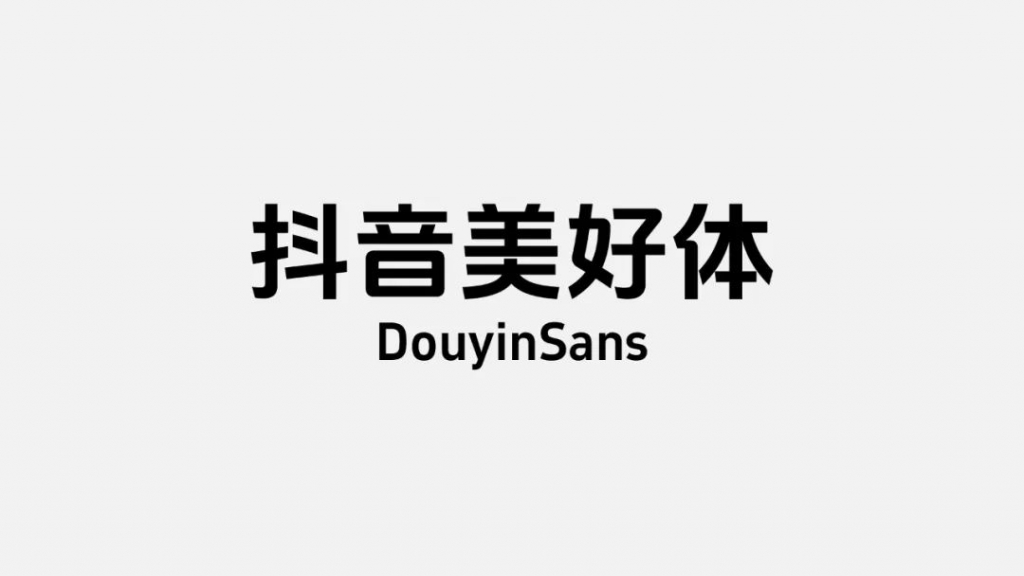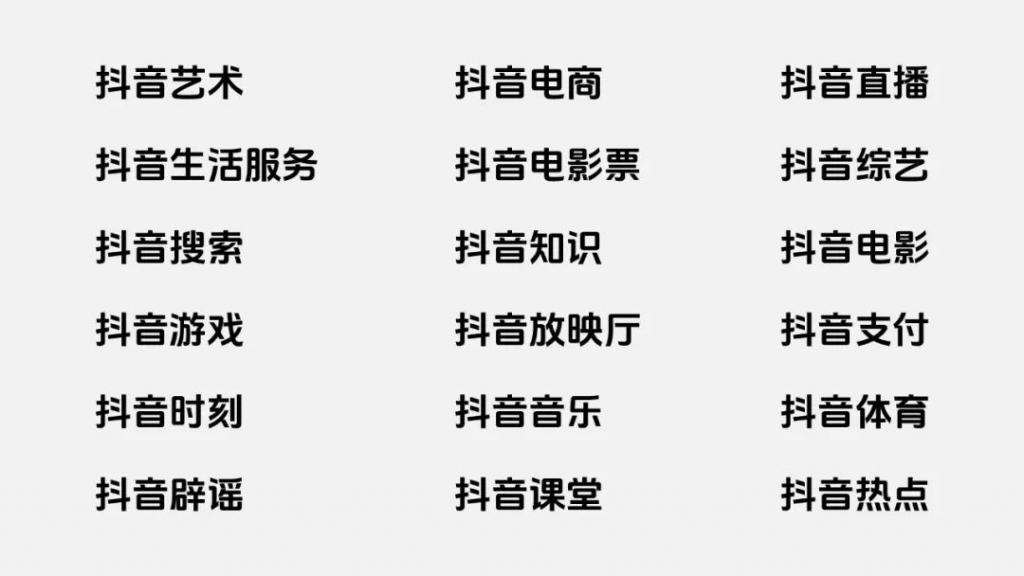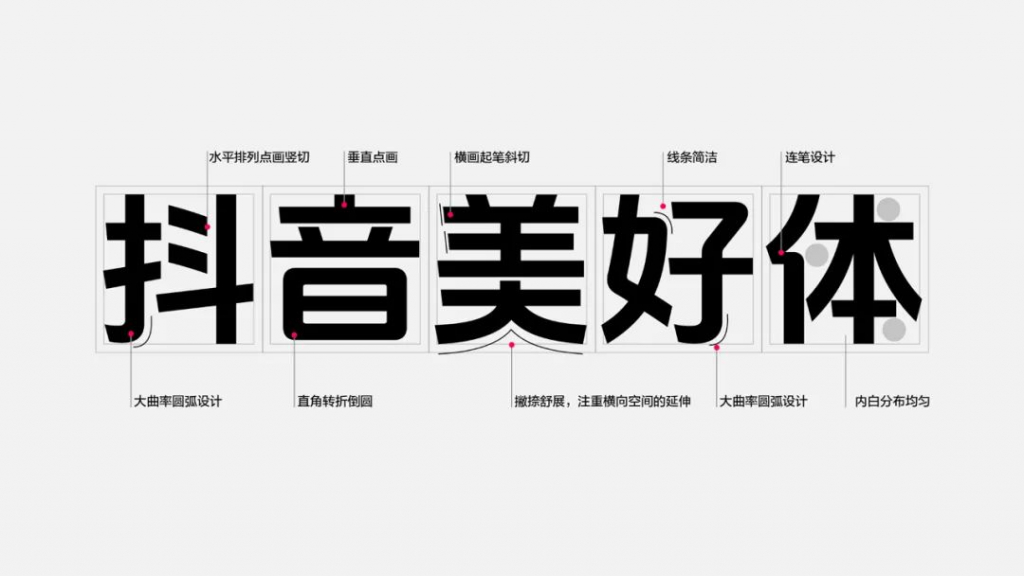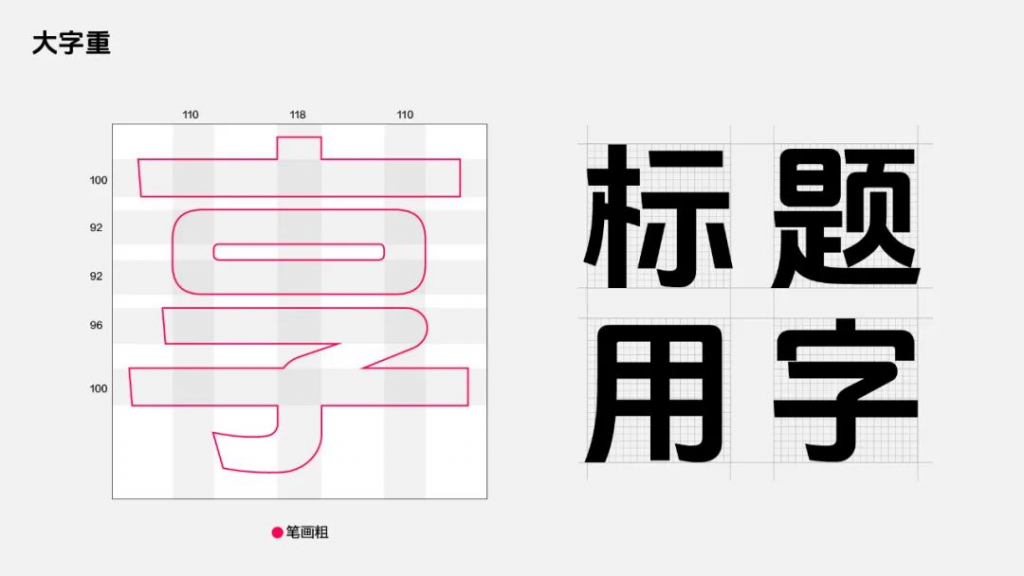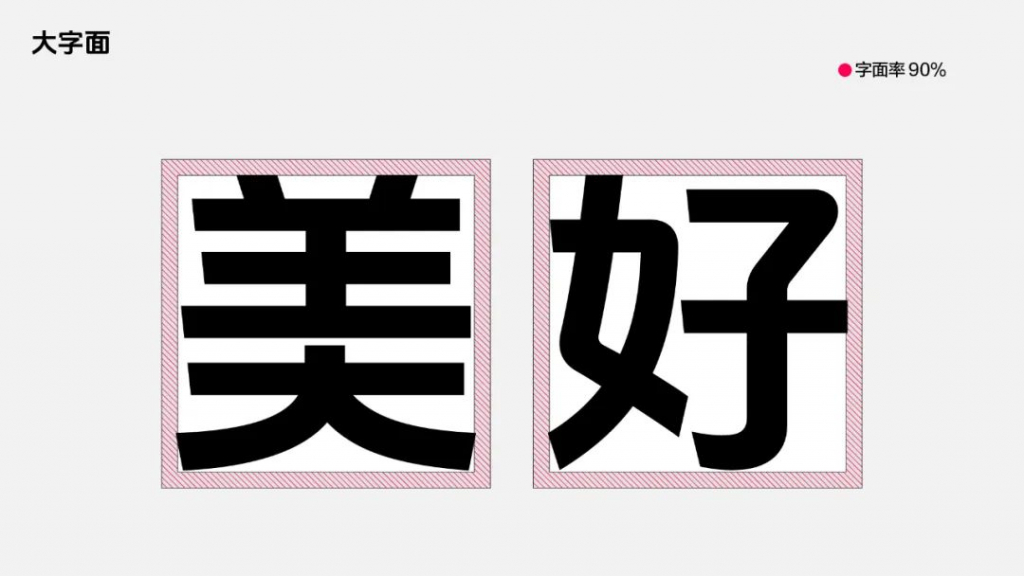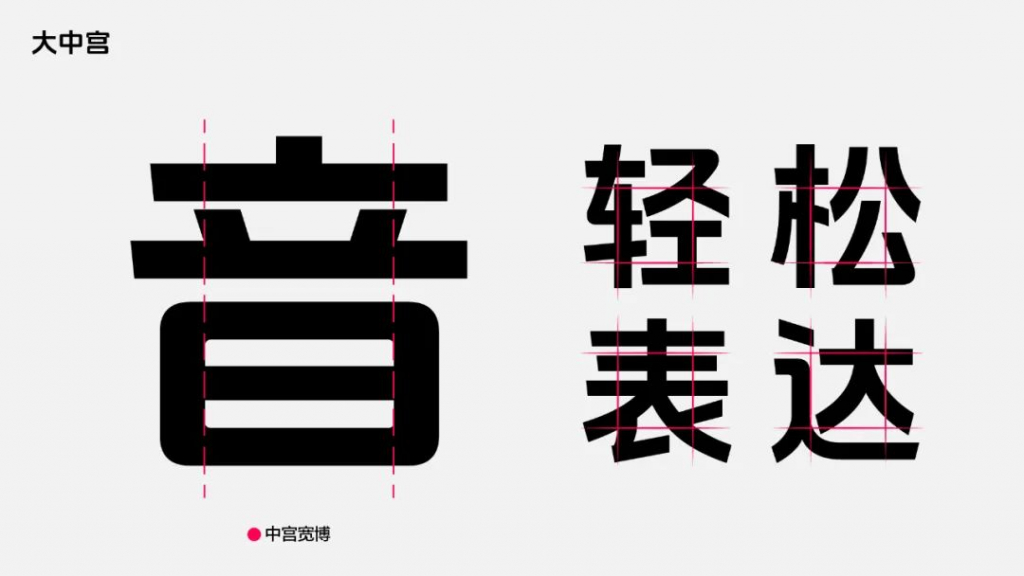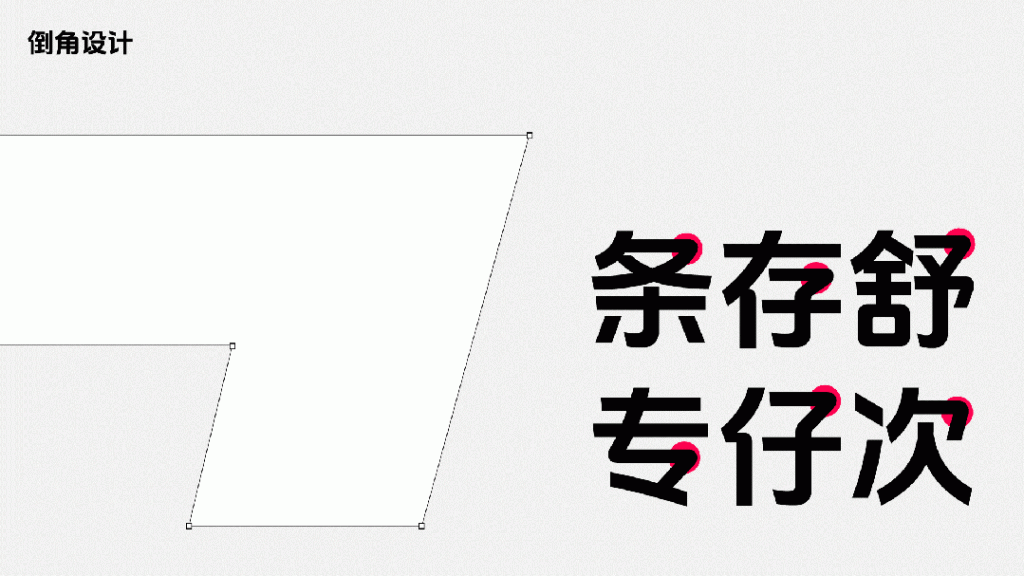
2023年,抖音已经从短视频平台发展为多体裁内容创作与分享平台,将优质内容带给用户的同时,更鼓励每一个人轻松创作与分享,去发现美好、传递美好。为了更好地传播“记录美好生活”的品牌理念,更好地满足品牌长远发展,打造优质的内容创作与产品体验,抖音体验设计中心与方正字库联合设计开发了一款简洁大方、清晰易读,同时兼具现代气质与人文属性的品牌定制字体——抖音美好体。
抖音美好体包含6763个中文字符,682个西文及数字符号,执行国家GB2312-80简体中文编码字符标准。作为品牌标准字体,抖音美好体将会率先用于抖音及其子品牌中,助力品牌视觉形象的统一,提升品牌的官方性、权威感。
差异化的品牌视觉形象,有助于塑造差异化的品牌调性。抖音美好体通过字体骨架搭建、笔画细节设计等细节,塑造出“沉稳内敛、自然舒适”的字体性格,与抖音带给人们“轻松、自然、舒适”的产品体验遥相呼应,传递出抖音独特的品牌调性与感受。
抖音美好体提取了“抖音”logo字体简约清新的风格特征,为适应标题场景的使用,被打造为笔画较粗的大字重字体;90%的大字面率,呈现出美观大方、清晰易读的视觉风格;大中宫设计,使得字体更加舒展饱满,字体具有极强的识别特征。
为构建品牌字体的独特性,抖音美好体的笔画细节采用了非常规的圆弧设计和倒角设计。弯勾笔画采用大曲率圆弧曲线,均匀顺滑的线条设计使得字体更流畅优美,更具视觉韧性。折笔笔画则在平衡字体易读性和识别度的基础上,采用了内直外弧的倒角方式,传递出一种“刚柔并济”的人文气息。
书法是中国传统文化的重要组成部分,笔画、结构、布局等元素都蕴含着丰富的文化内涵和审美价值。抖音美好体将传统书法文化中的书写感、流畅感与现代字体设计相结合,借鉴了行书中连笔书写一气呵成的精髓,形成独特的连笔设计,将“灵动流畅、收放自如”的视觉体验与抖音“轻松、自然、舒适”的产品体验融为一体。
抖音美好体同样借鉴书法中笔锋的概念,将发笔时顺势落笔、笔锋显露在外的“露锋”笔法,转换为横笔斜切的设计手法,在保留书写感的同时,增加字体的视觉变化节奏。
为了满足抖音全生态全场景的标题使用需求,抖音美好体搭配了具有几何风格的西文字符,字形简洁干练、现代时尚,同时在细节上延续了中文的圆弧及横笔画斜切的特征,中西文匹配使用时呈现出一致的视觉气质。
为了更好地以品牌赋能产品与业务,满足抖音端内不同场景的字体应用诉求,抖音体验设计中心团队将西文及数字字符拓展至5种不同粗细、宽窄,提升了字体与产品场景的适配度。除了全量上线抖音端内核心场景以外,抖音美好体已被广泛用于抖音市场传播场景,同时已内嵌于剪映、醒图等产品,抖音美好体将不断地助力业务发展。